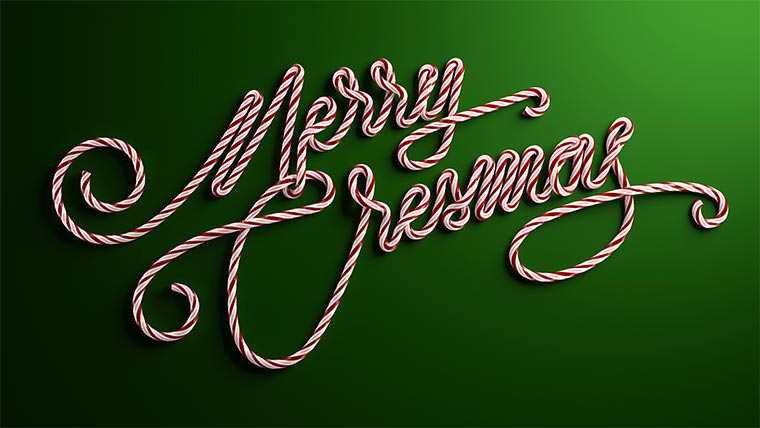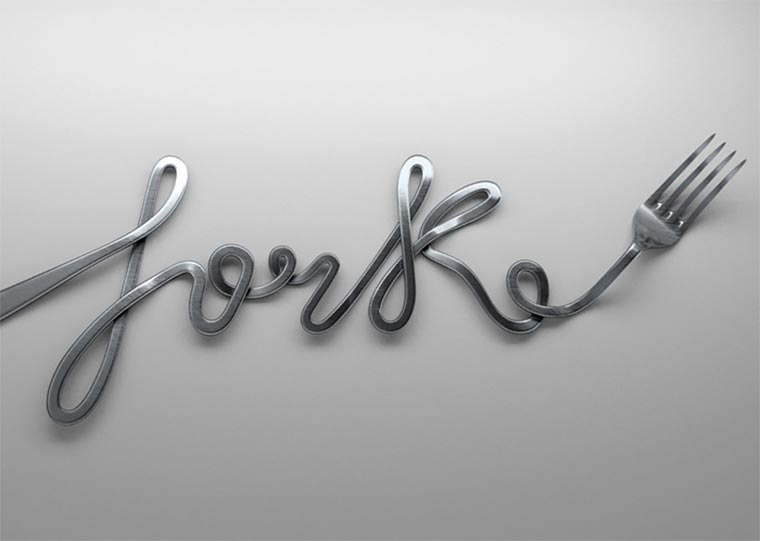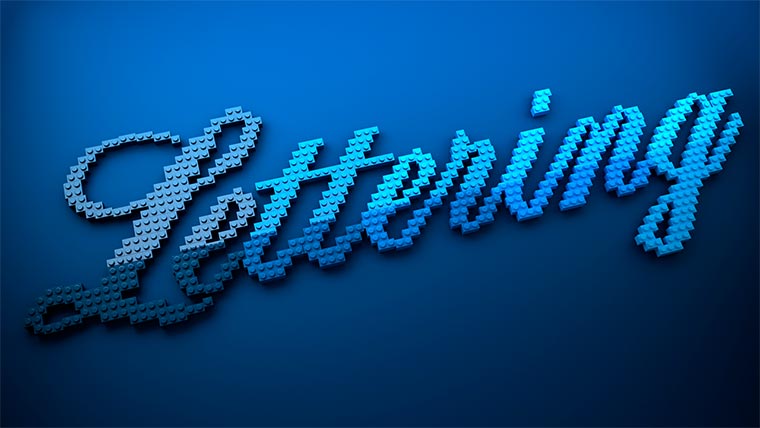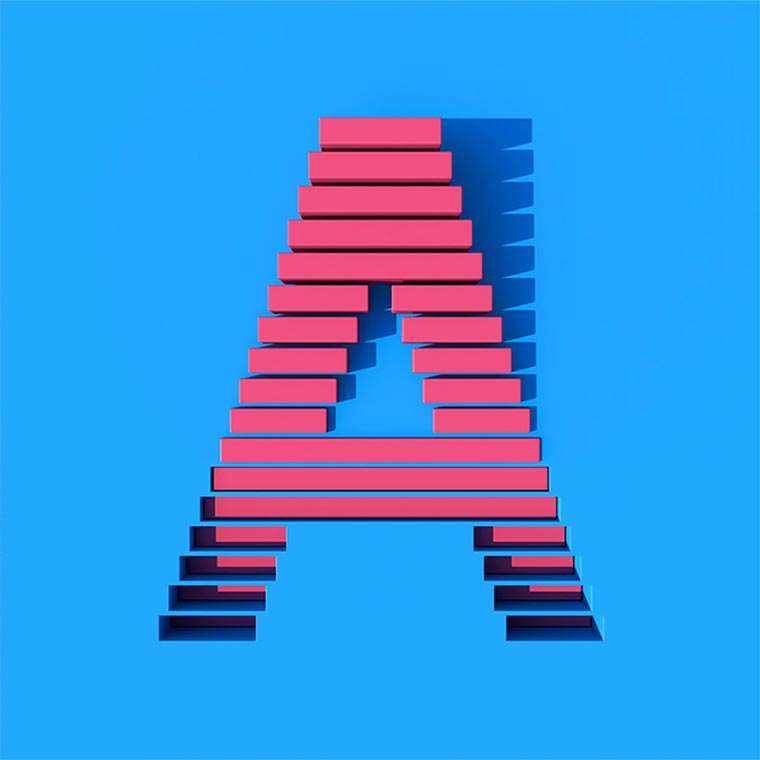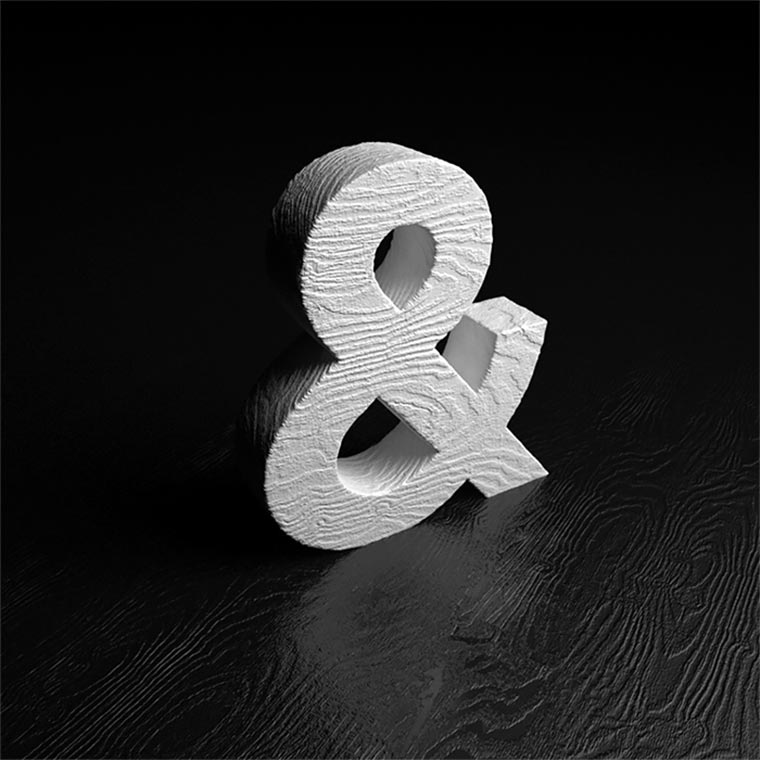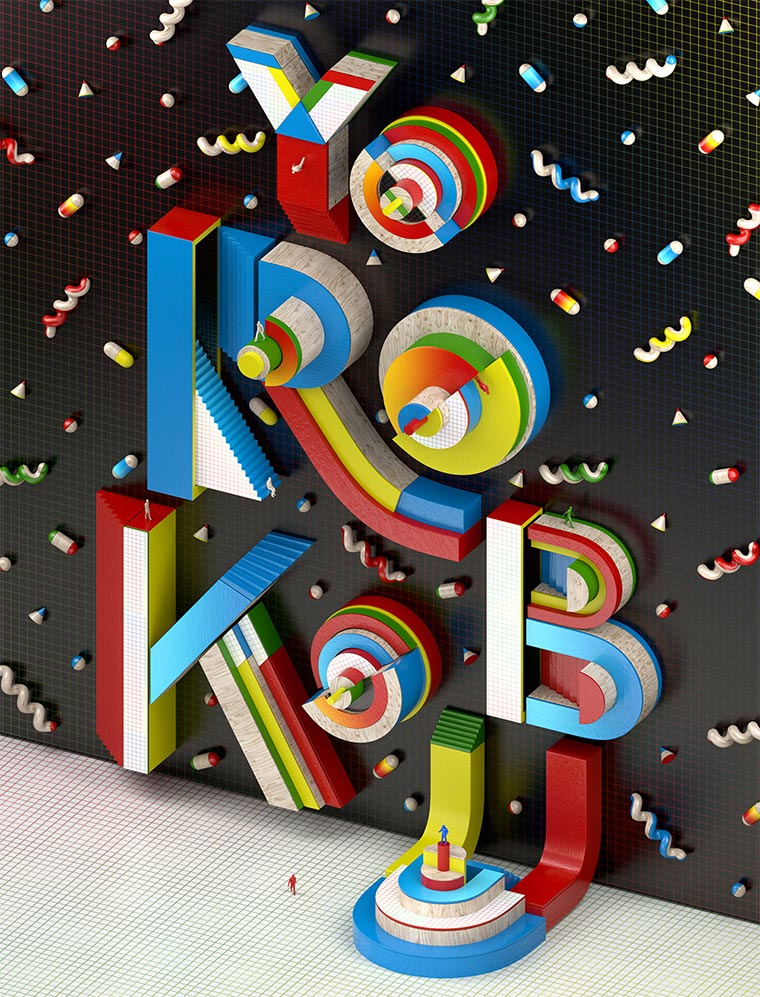
Kreative 3D-Darstellungen
Typografie: Alejandro López Becerro
Typografie: Alejandro López Becerro Becerro_01
Alex ist Grafik-Designer aus Madrid und eigentlich gerade hauptsächlich im Bereich Motion tätig. Ganz nebenbei zaubert er aber wunderbare 3D-Typografien, die ich euch einfach nicht vorenthalten kann. Sehr kreative Arbeiten, die auch ungemein detailliert ausgearbeitet worden sind.